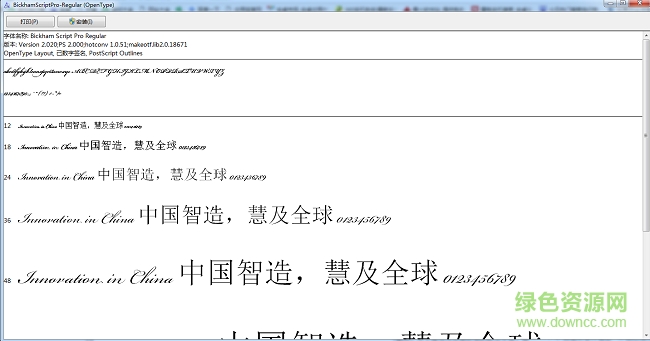
bickhamscriptpro regular字體
bickham script pro regular字體是一款漂亮的英文花體字體,線條優(yōu)美流暢,字形豐富多變,裝飾性強,筆畫有一定斜度,字母緊密,綠色資源網(wǎng)還有超多個性英文字體隨你下載使用!
花體字體介紹
花體英文是一種英文字體類別,這種類別為國內(nèi)書法,國外并沒有這種字體分類。一般認為是copperplate字體、圓體字或者斯賓塞體,多見于電影書信和封面裝飾。
bickham script pro regular
花體英文特色
1.粗細變化
2.游絲
3.排版